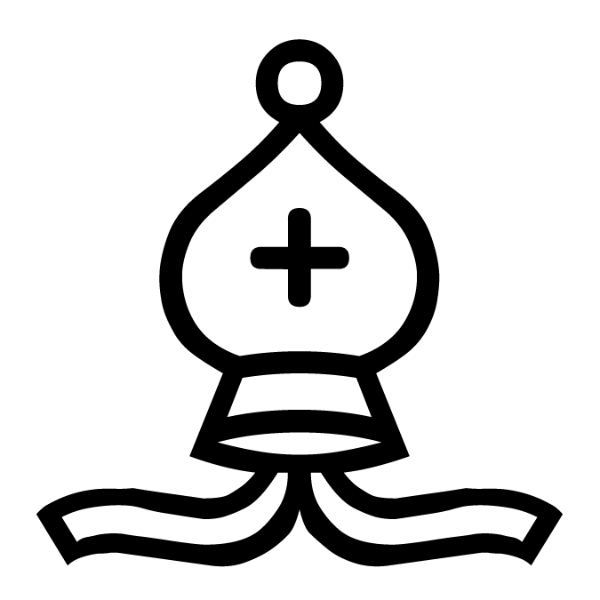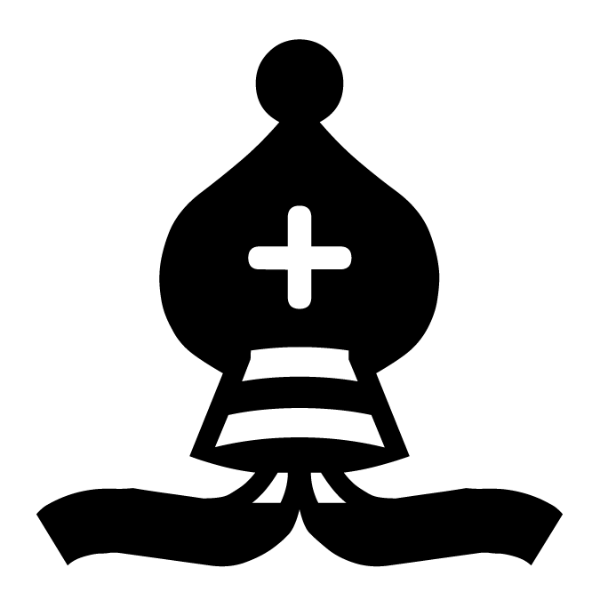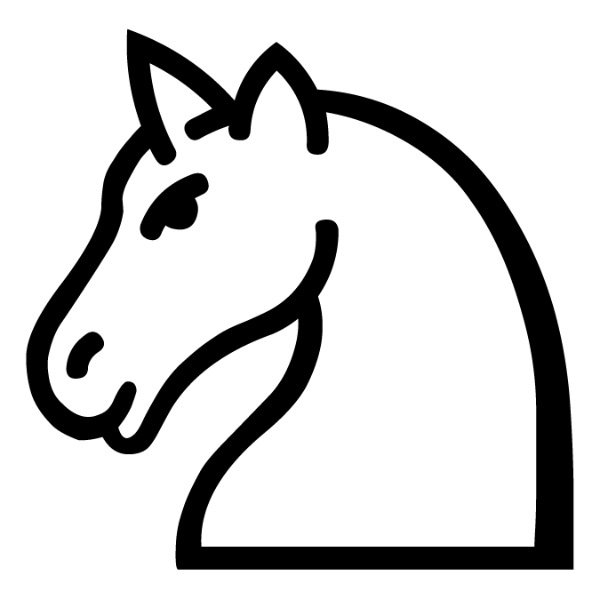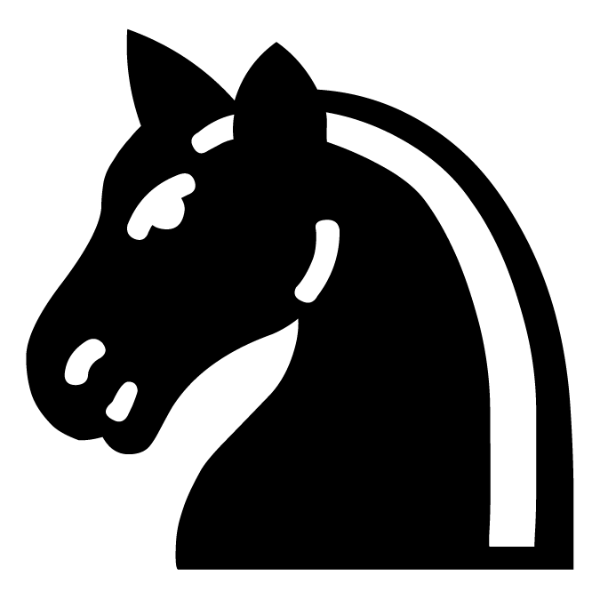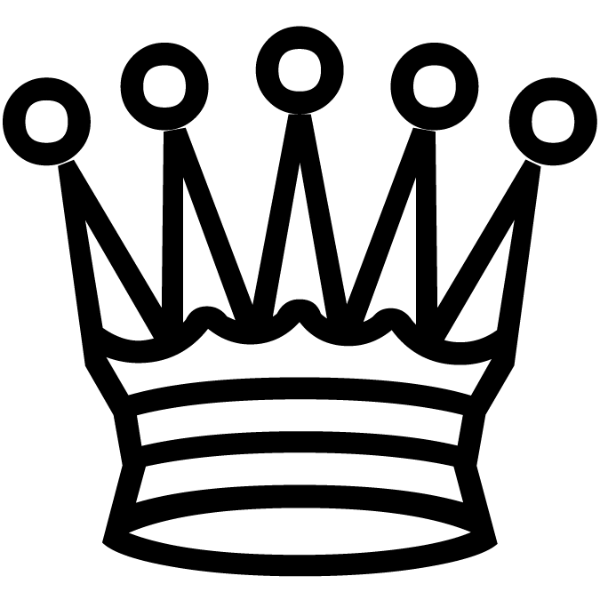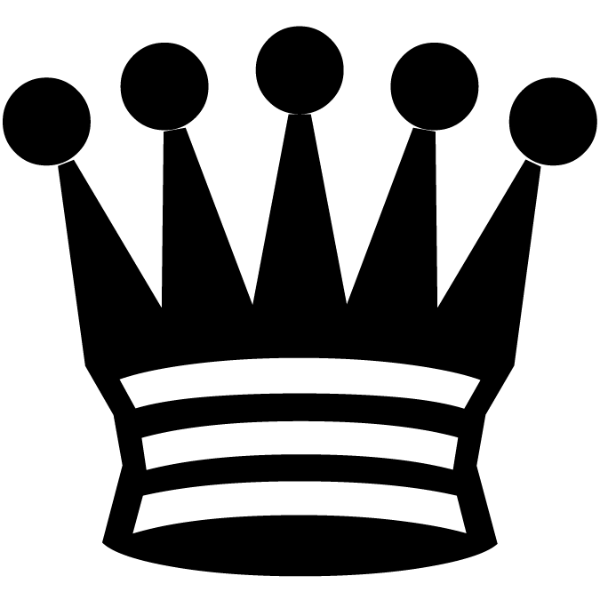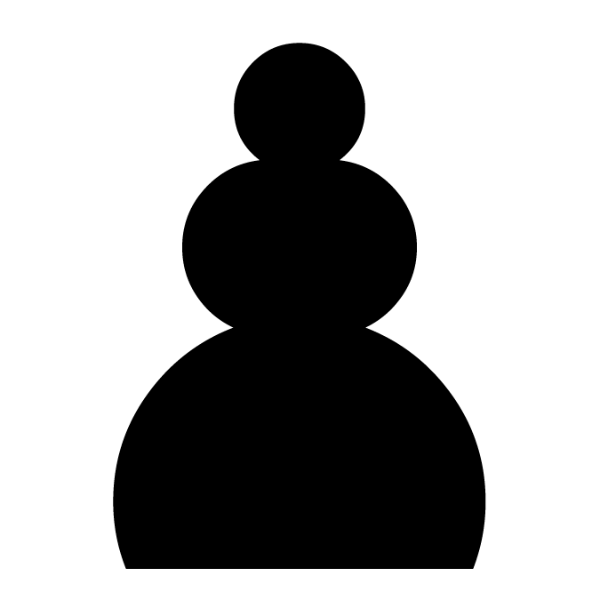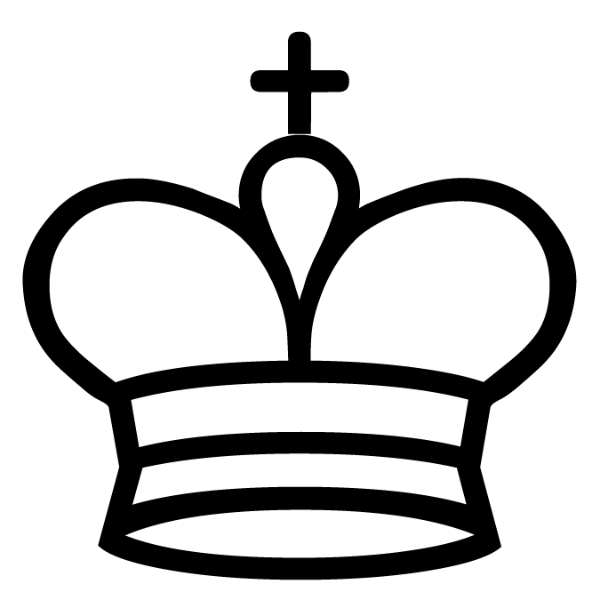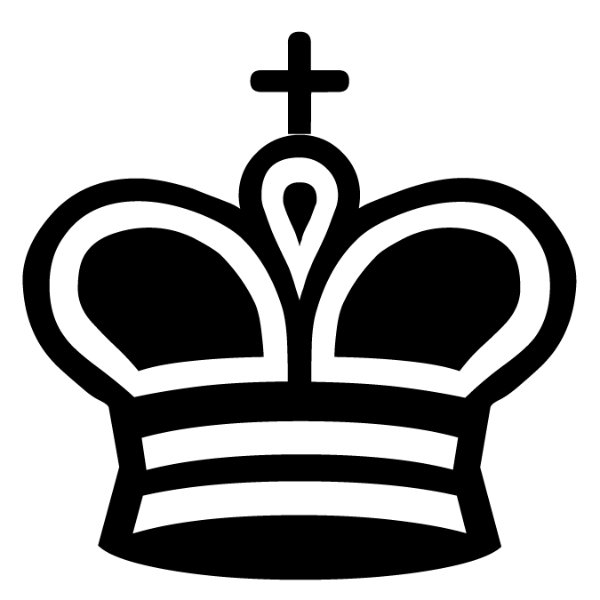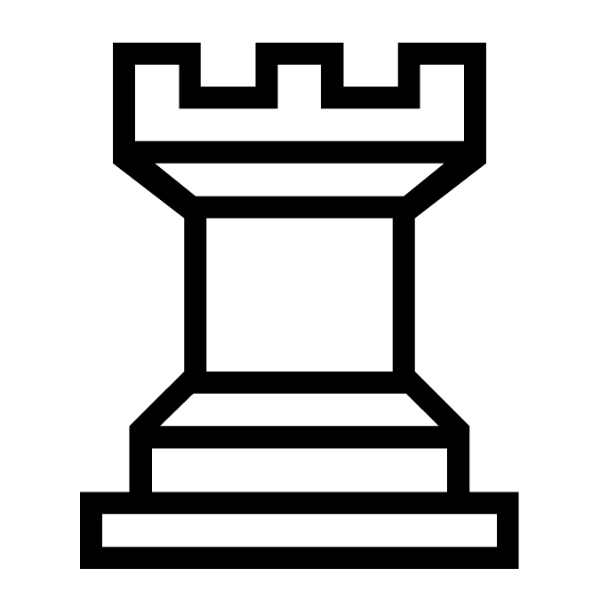
Chess Mérida es una fuente de ajedrez clásica, clara y elegante, ideal para crear diagramas, documentos y materiales relacionados con el ajedrez. Sus piezas tienen un diseño limpio, fácil de reconocer y sin distracciones visuales innecesarias.
Juego de ajedrez con la fuente Chess Mérida: